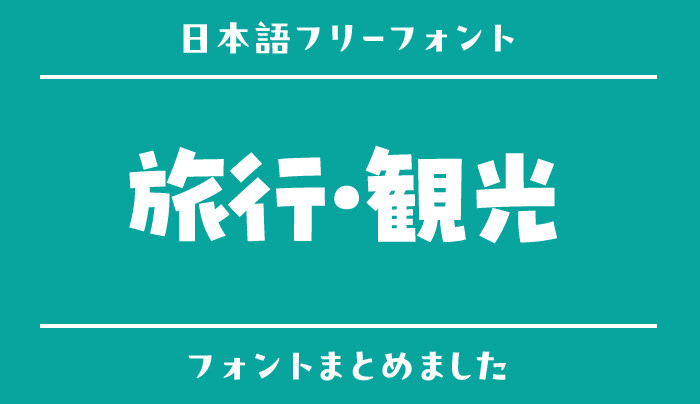
海辺の旅、鉄道で巡る街歩き、思い出を残す旅日記。旅行・観光のデザインは、行き先の雰囲気に合うフォントを選ぶと、写真だけでは伝えきれない空気まで表現できます。一方で、地図や時刻、施設情報には迷わず読める文字が欠かせません。
今回はフォントラボから、旅行・観光に取り入れたい日本語フリーフォントを15個紹介します。パンフレットや旅のしおり、写真のコメントなど、用途に合わせて選んでみてください。地名には珍しい漢字もあるため、収録文字の確認は完成する名称で行いましょう。
旅の行き先と制作物に合わせて選ぶ日本語フリーフォント
なぎの
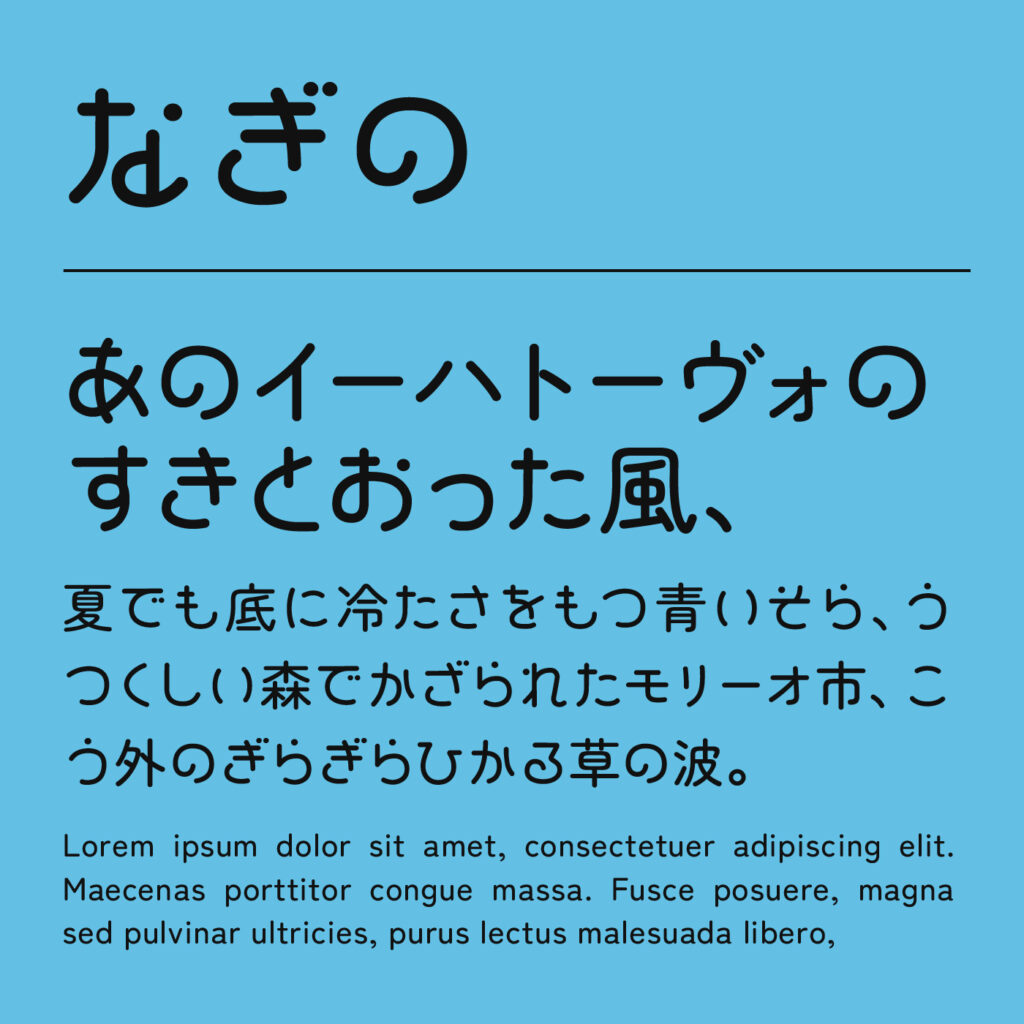
| おすすめの場面 | 海辺の旅の表紙/港町の紹介/海の写真へのコピー |
海を感じるかなのフォントで、行き先を印象づける。
「なぎの」は、海や船、窓を思わせるモチーフを取り入れたかなが特徴のフォントです。海辺の旅や港町の紹介に使うと、短い言葉にも場所の気配を添えられます。すべての文字が装飾されるわけではないので、使う地名やコピーを試して選ぶのがおすすめ。細かな施設情報には別のフォントを使い、旅の表題を主役にしましょう。
国鉄っぽいフォント
| おすすめの場面 | 鉄道旅行の表紙/駅巡りの記録/路線を扱う特集 |
駅の看板を思わせるフォントで、鉄道旅の気分に。
「国鉄っぽいフォント」は、昔の国鉄の駅名表示を思わせる、手仕事のやわらかさがあるフォントです。鉄道旅行の表紙や駅巡りの記録に使うと、車窓やホームの写真と馴染みます。公式の国鉄フォントではなく、その雰囲気を楽しむものとして選びましょう。列車の時刻や乗換案内は標準的なフォントで組み、演出と実用情報を分けるのがおすすめです。
いろは角クラシック
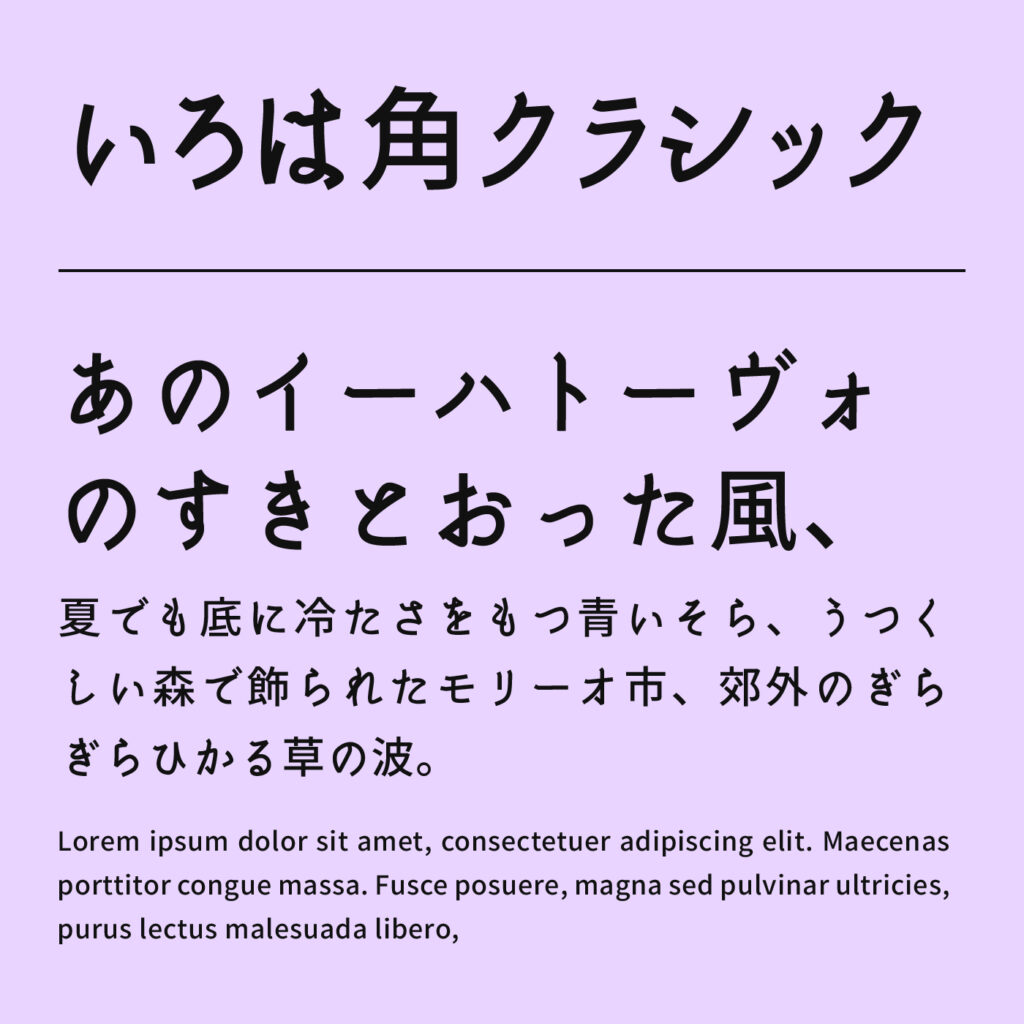
| おすすめの場面 | 歴史ある街の案内/街歩きマップの見出し/観光冊子 |
古風なかなのフォントで、街の歴史をさりげなく。
「いろは角クラシック」は、古風なかなとゴシックの骨格を組み合わせたフォントです。歴史ある商店街や建物を紹介する冊子で、懐かしさを出しながら情報も伝えたいときにおすすめ。大げさな装飾フォントを使わず、街の写真を中心に構成できます。地図の小さな文字にする場合は、独特なかなの形が読み取れるサイズか確認しましょう。
いろはマル
| おすすめの場面 | 温泉街の案内/散策のしおり/家族旅行の表紙 |
丸いフォントに、どこか懐かしい街歩きの空気を。
「いろはマル」は、丸みのある輪郭に古風なかなの表情が加わったフォントです。温泉街や小さな町の散策など、ゆっくり歩く旅の案内に合います。子どもっぽくしすぎず親しみを出せるため、大人向けのしおりにもおすすめ。写真の説明は落ち着いた太さにし、見出しとの差を付けると、フォントのやさしさを活かした紙面になります。
しっぽり明朝
| おすすめの場面 | 文化を巡る旅/宿の紹介/観光パンフレット |
端正な明朝フォントで、旅先の魅力を丁寧に。
「しっぽり明朝」は、やわらかな角と墨だまりが、落ち着いた雰囲気を作る明朝フォントです。文化施設や宿を紹介するパンフレットで、写真と文章を丁寧に見せたいときに向いています。太さを変えて見出しと本文を揃えると、フォントを増やさず冊子全体を統一できます。珍しい地名や施設名は、正式な表記で表示できるか確認しましょう。
はんなり明朝
| おすすめの場面 | 庭園や寺社の紹介/散策コース/旅の挨拶文 |
しなやかなフォントで、落ち着いた散策に。
「はんなり明朝」は、優雅なかなの流れが、穏やかな観光案内に合う明朝フォントです。庭園や寺社、季節の景色を扱う紙面で、硬すぎない上品さを出したいときにおすすめ。短いコピーだけでなく、数行の紹介文にも表情が出ます。交通情報は別のフォントで明快にまとめ、風景を味わう文章にはゆったりした行間を取りましょう。
源雲明朝
| おすすめの場面 | 旅のエッセイ/風景写真集/地域の読み物 |
墨の温度があるフォントで、旅の余韻を残す。
「源雲明朝」は、線の交わりに墨だまりを感じる明朝フォントです。風景写真に添える文章や旅のエッセイなど、急がず読んでほしい内容におすすめ。すっきりした案内用フォントとは違い、記憶や土地の空気を伝える役割で選べます。文章を写真の上に詰め込むより、余白を設けて読み物として組むと、静かな表情が引き立ちます。
まちのてちょうフォント
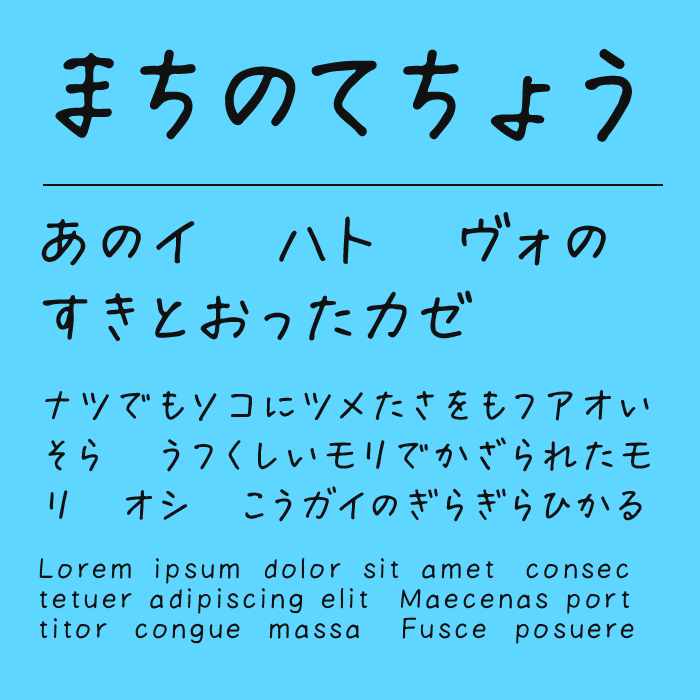
| おすすめの場面 | 街歩きのひと言/旅ノートの見出し/かなのコメント |
手帳のようなフォントで、個人の発見を添える。
「まちのてちょうフォント」は、手書きの揺れやインクのたまりが、旅先で書いたメモを思わせるフォントです。写真に添える短い感想や街歩きノートの見出しにおすすめ。無料版には漢字が含まれないため、地名や施設名を丸ごと組む用途では確認が必要です。かなのひと言をこのフォントにし、正確な場所の情報は漢字対応のフォントで添えると使いやすくなります。
あるぺんフォント
| おすすめの場面 | 自然の旅の記録/旅日記の表紙/景色へのコメント |
筆圧のあるフォントで、体験した人の声に。
「あるぺんフォント」は、ペンの筆圧やかすれが感じられる手書きフォントです。自然の中で過ごす旅や、歩いて見つけた景色の記録に、実感のあるひと言を添えられます。無料版の漢字は教育漢字が中心なので、地名の収録には特に注意しましょう。装飾用のフォントとして短く使い、旅程の情報を読みやすい文字で分けると、手作り感と実用性が両立します。
きろ字
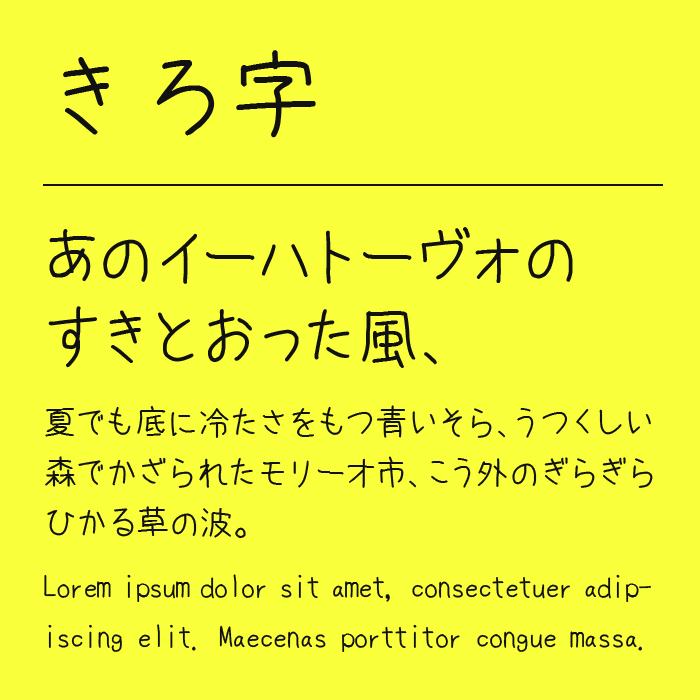
| おすすめの場面 | 旅日記/写真のキャプション/思い出の小冊子 |
整った手書きフォントで、思い出を読み物に。
「きろ字」は、手書きらしさを残しつつ、形が落ち着いているフォントです。写真の感想だけでなく、その日の出来事を少し長く書く旅日記にもおすすめ。表紙用の目立つフォントより、文章から人柄を感じさせる役割に向いています。複数の写真に使う場合は文字サイズと配置を揃え、コメントが写真を覆いすぎないようにしましょう。
LINE Seed JP
| おすすめの場面 | 旅程表/施設案内/観光サイトの本文 |
親しみやすいフォントで、旅の情報を整理。
「LINE Seed JP」は、整った形と穏やかな印象を持つ日本語フォントです。旅程表や施設案内、観光サイトの文章など、繰り返し確認する情報におすすめ。個性的なタイトルフォントと組み合わせても、ページ全体を硬くしすぎず支えられます。太さを使い分けて時刻や場所を目立たせ、説明文との違いを付けると、移動中にも読み取りやすい案内になります。
Noto Sans
| おすすめの場面 | 交通案内/営業時間/地図内のラベル |
定番のフォントで、迷いたくない情報を明確に。
「Noto Sans」は、クセの少ないゴシックフォントで、日本語の制作にはNoto Sans JPなどを選びます。交通案内や営業時間のように、雰囲気より正確な読み取りを優先したい部分におすすめ。地図では文字の太さを揃え、背景との明暗差を確保しましょう。見出しフォントを別にする場合も、重要な数字が小さくならないように組むことが大切です。
Rounded M+
| おすすめの場面 | 親子旅行のしおり/体験施設の案内/観光マップ |
丸いフォントで、家族向けの案内をやさしく。
「Rounded M+」は、丸みのある輪郭が、親しみやすい旅の紙面を作るフォントです。親子旅行のしおりや体験施設の案内など、気軽に読んでもらいたい制作物に向いています。丸みの度合いを比べ、写真やイラストとのバランスで選ぶのがおすすめ。楽しげな見出しフォントを使う場合も、地図や料金欄は余白を残し、数字を明快に見せましょう。
アプリ明朝
| おすすめの場面 | 旅先の紹介文/小冊子の本文/宿の案内 |
やわらかな明朝フォントで、紹介文を読みやすく。
「アプリ明朝」は、丸い止めやウロコが、明朝らしい品のよさを穏やかに見せるフォントです。宿や地域の紹介を数段落で伝える小冊子におすすめ。強い見出しフォントの下でも、本文の印象をやわらげられます。細い横線が見えにくくならないよう、印刷物では実寸で確認し、行間と背景のコントラストを調整しましょう。
モボ
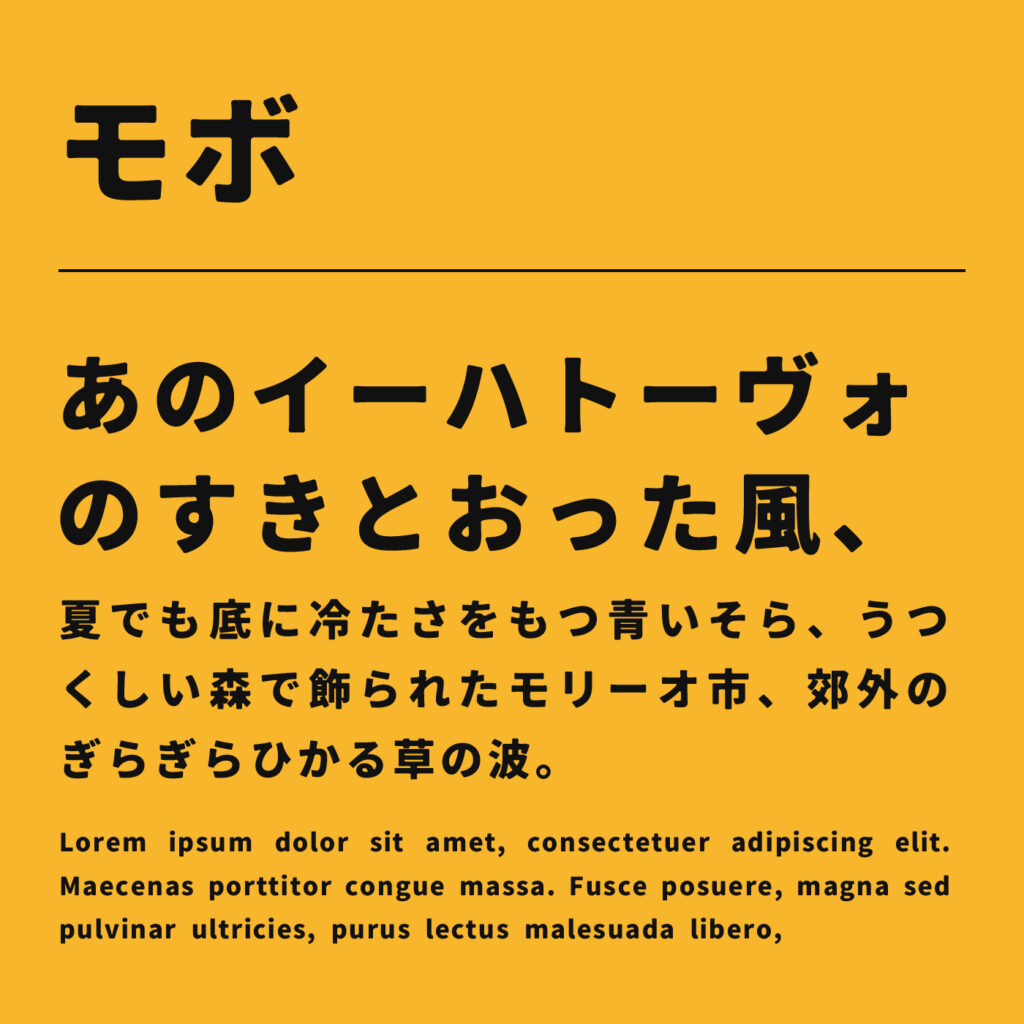
| おすすめの場面 | 都市の観光案内/ショップ巡り/週末旅行の見出し |
現代的なフォントで、街の情報を軽快に。
「モボ」は、すっきりしたゴシックに丸みがあり、ほどよく親しみのあるフォントです。都市のショップ巡りや週末旅行など、情報量のある案内を軽快に見せたいときにおすすめ。太さを変えることで、店名と紹介文を少ないフォント数でまとめられます。写真の多いページでは装飾を増やしすぎず、見出しの位置を揃えて回遊しやすく整えましょう。